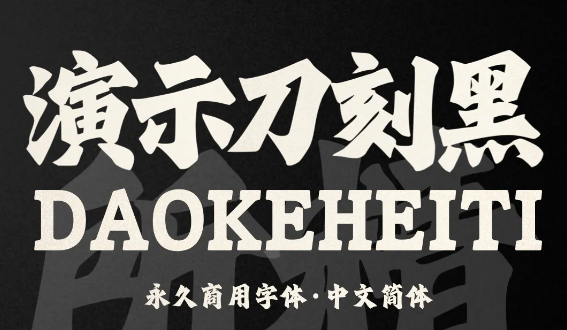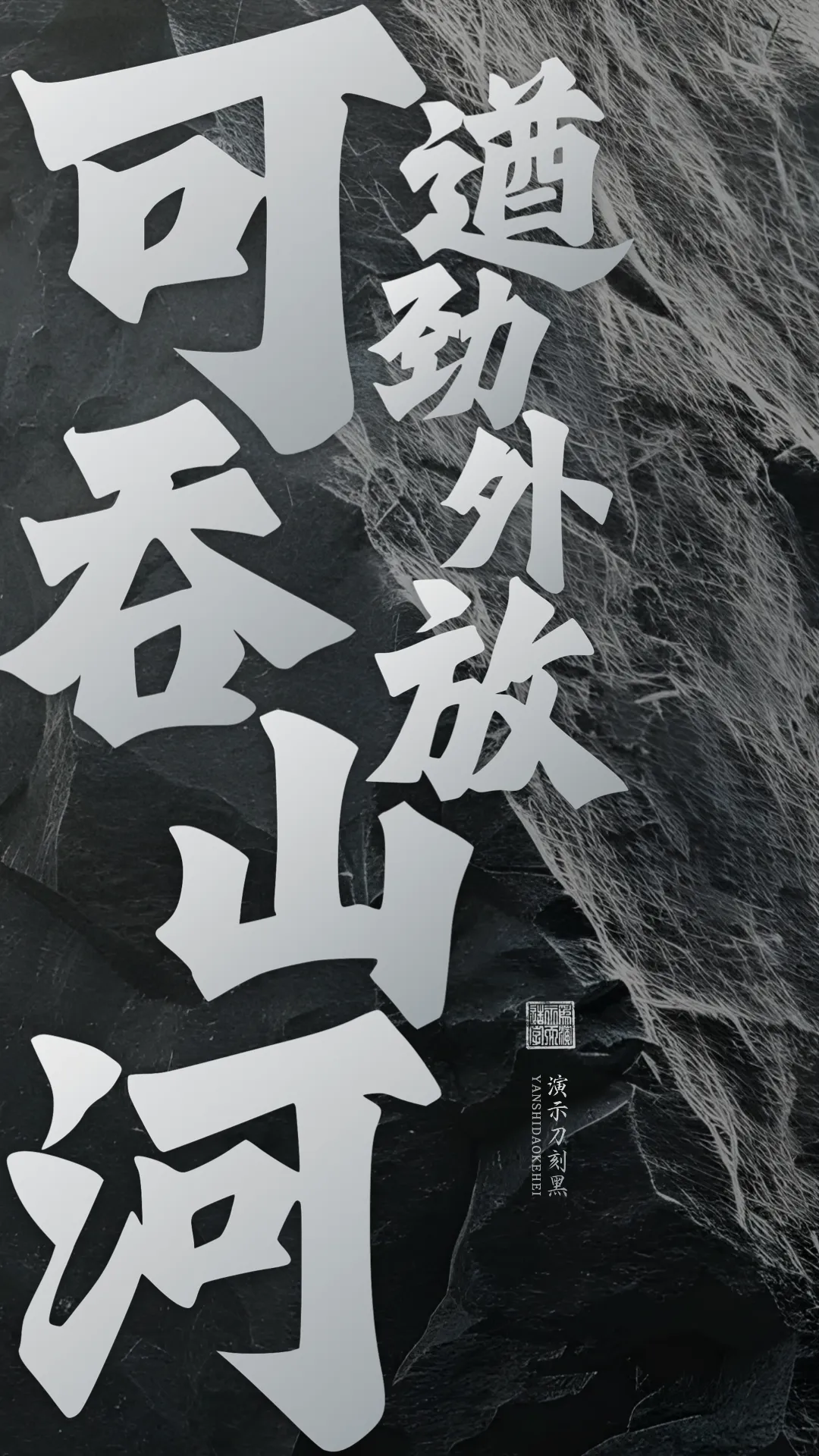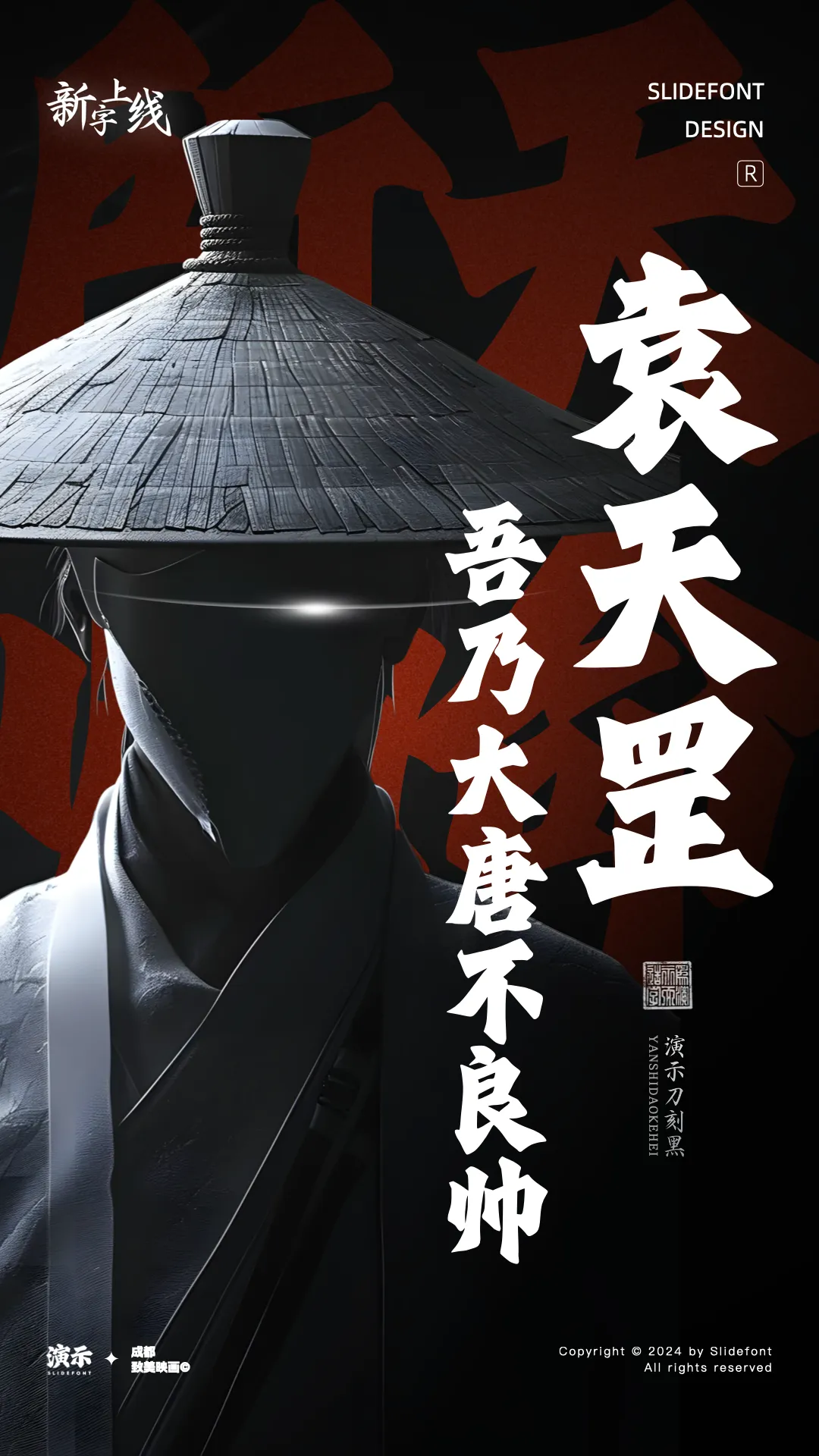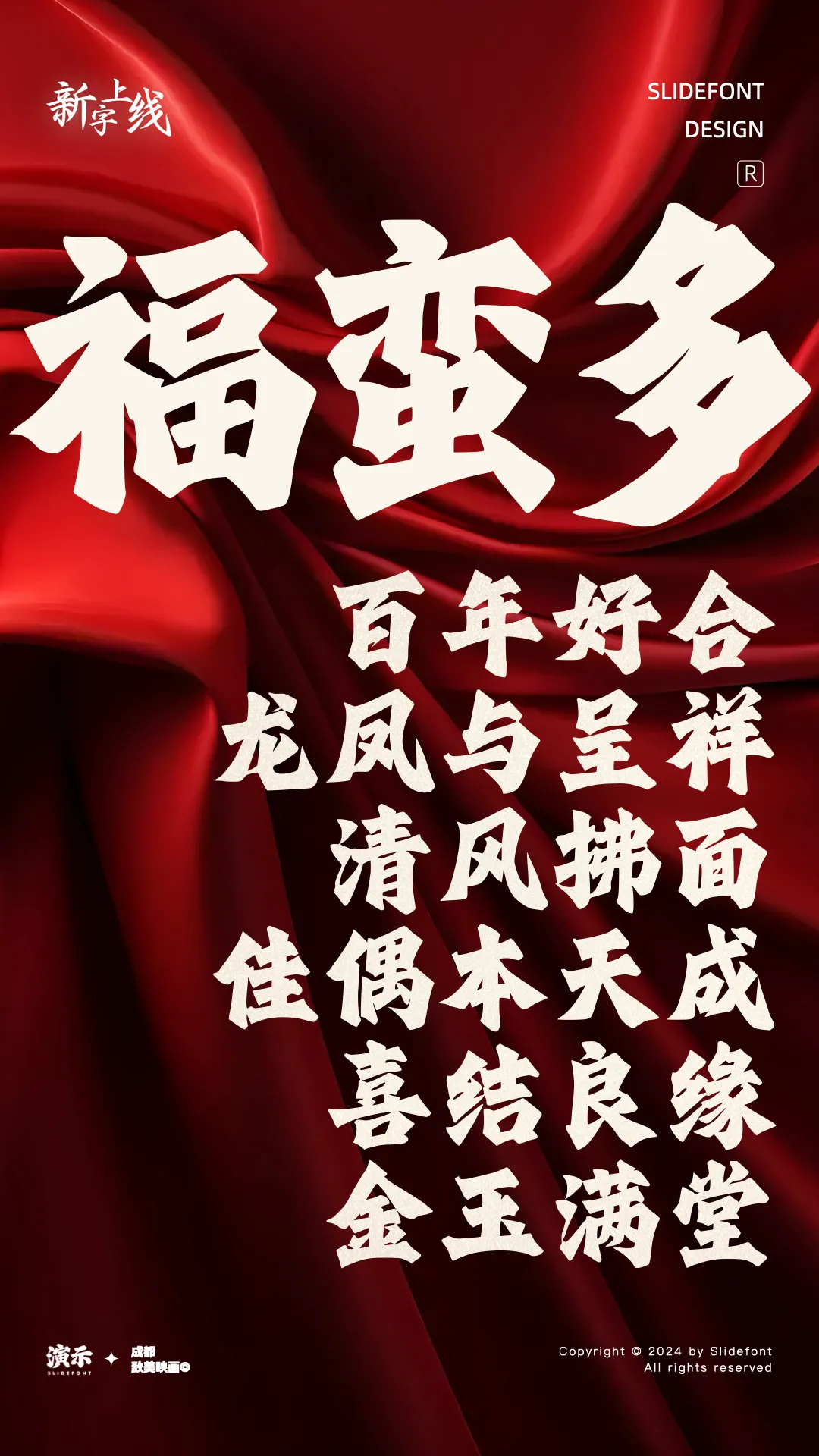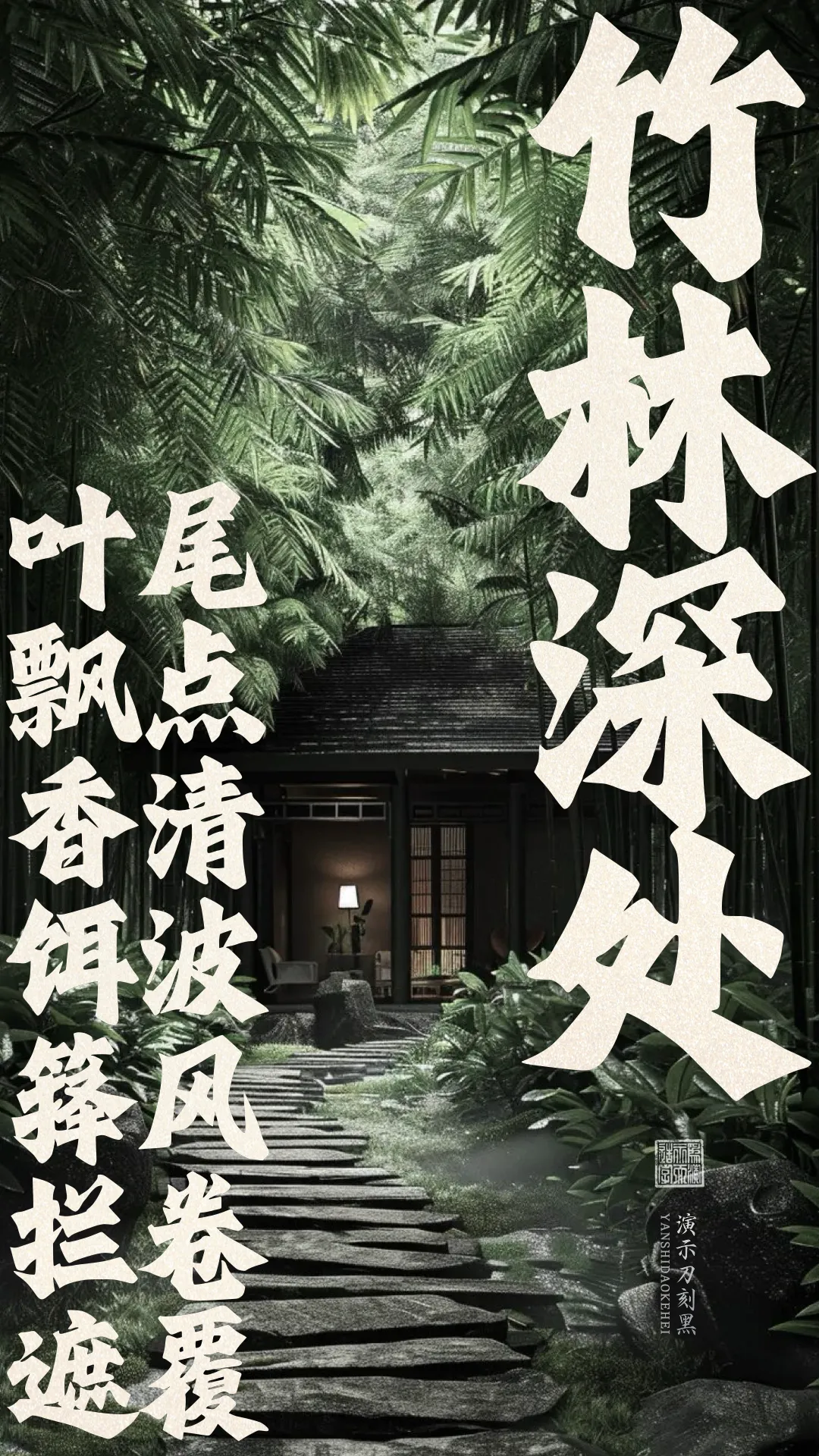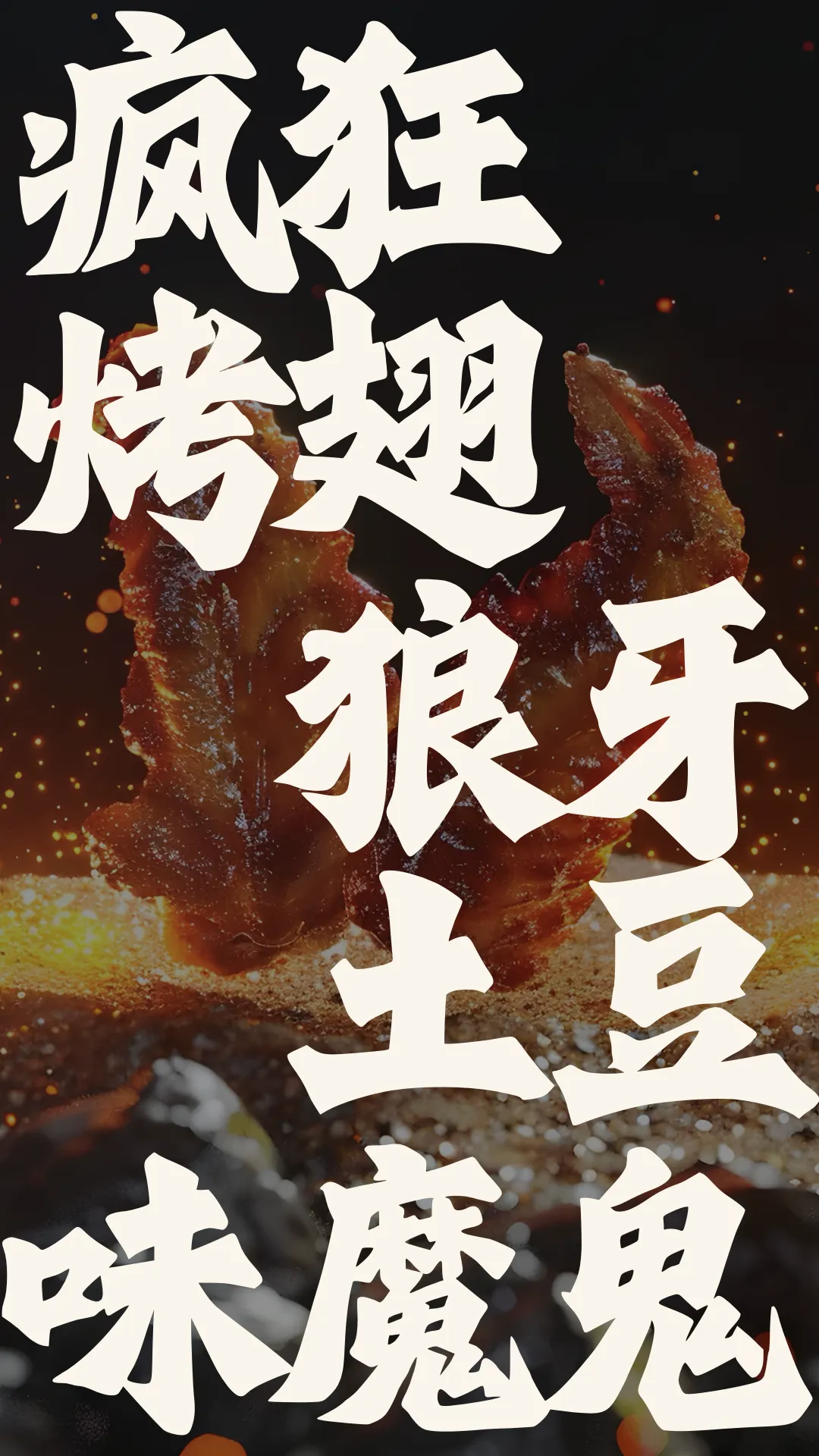
演示刀刻黑是 演示字体 推出的一款创意美术字。创作灵感源自北魏刻石,旨在适应现代商业环境及屏显用字的需求,笔划造型略带古朴拙气,行笔厚重外放自然,整体给人以厚重凌厉之感,使其在展现艺术魅力的同时,又能满足多种商业宣传的实际需求,适用于幻灯片演示、影视字幕、品牌广告及营销等领域。
字体风格:创意美术字